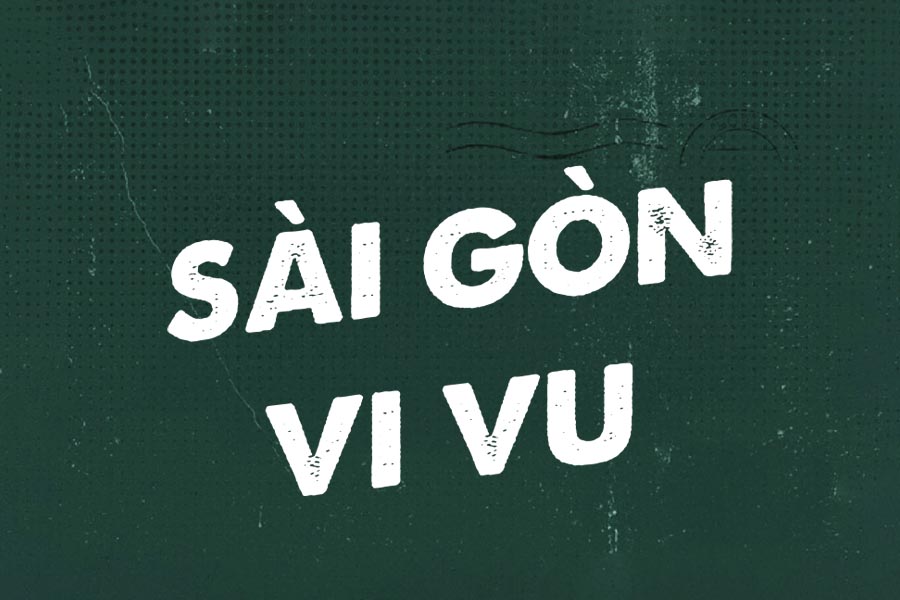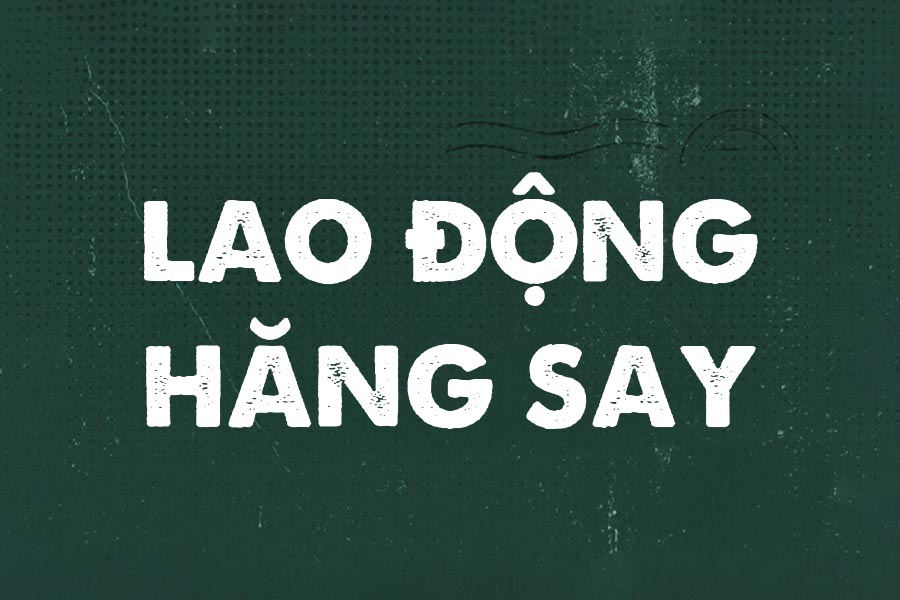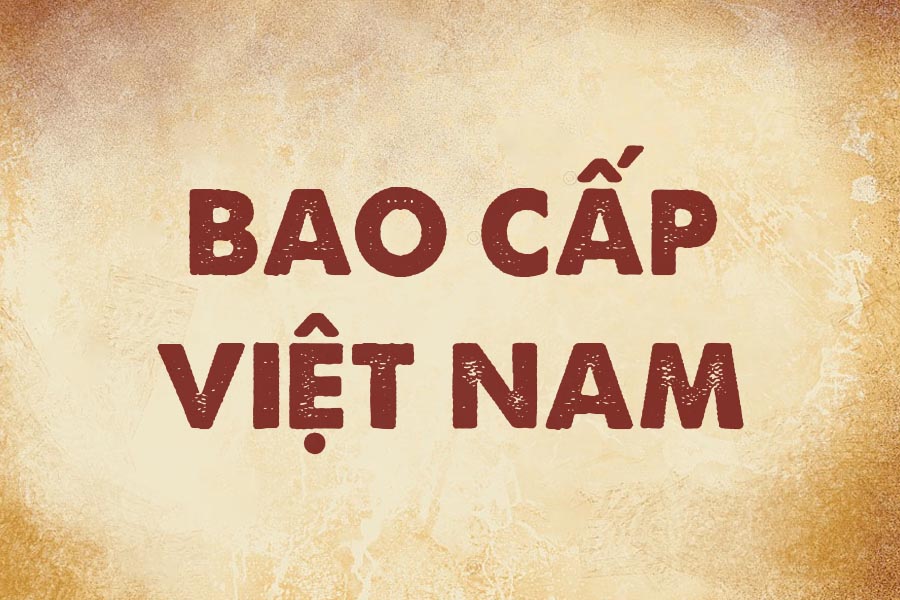
Bạn đang tìm một font chữ xưa, mang hơi thở thời kỳ bao cấp, gợi nhắc những tấm poster tuyên truyền hay khẩu hiệu treo đầu ngõ? Hãy thử ngay SVN-A Love of Thunder – một trong những font hoài cổ nổi bật nhất, mang đậm chất retro Việt Nam, được Việt hóa chỉn chu và miễn phí tải về.
Giới thiệu font SVN-A Love of Thunder
SVN-A Love of Thunder là font chữ display không chân, thiết kế theo phong cách áp phích tuyên truyền thời bao cấp với những nét chữ in đậm, rắn rỏi và hiệu ứng rách nhẹ như in trên giấy cũ. Các đặc điểm nổi bật:
• Toàn bộ chữ in hoa, tạo cảm giác cổ điển và cứng cáp.
• Nét chữ dày, đều, dễ đọc, lý tưởng cho tiêu đề hoặc slogan.
• Hiệu ứng grunge nhẹ, mô phỏng chất liệu in ấn thời xưa.
• Việt hóa hoàn chỉnh, hỗ trợ đầy đủ dấu tiếng Việt và ký tự đặc biệt.
Font chữ xưa gợi nhớ thời bao cấp
Không đơn thuần là một kiểu chữ, SVN-A Love of Thunder còn là một biểu tượng của ký ức. Font này gợi nhắc về giai đoạn bao cấp, nơi những câu khẩu hiệu như “Lao động là vinh quang”, “Đoàn kết là sức mạnh” được in đậm trên tường nhà máy, trường học, hợp tác xã…
Đó là lý do vì sao đây là font hoài cổ được rất nhiều designer lựa chọn cho:
• Poster cổ động, băng rôn tuyên truyền
• Bìa sách lịch sử, ấn phẩm văn hóa truyền thống
• Thiết kế vintage: tem phiếu, bao bì xưa, bảng tên hợp tác xã
Ứng dụng phong cách retro bao cấp trong thiết kế
SVN-A Love of Thunder là lựa chọn lý tưởng cho các thiết kế mang hơi thở xưa cũ, hoài cổ và thời kỳ bao cấp, cụ thể như:
• Poster tuyên truyền, tranh cổ động: Tái hiện khẩu hiệu như “Lao động là vinh quang”, “Đoàn kết là sức mạnh”.
• Bìa sách lịch sử – văn hóa: Phù hợp với sách nghiên cứu, hồi ký, tư liệu xưa.
• Ấn phẩm bảo tàng – triển lãm: Dùng cho tiêu đề, bảng chú thích, thiết kế trưng bày mang phong cách cổ điển.
Banner, băng rôn trường học: Rõ nét, dễ đọc, đúng chất tuyên truyền giáo dục thời bao cấp.
Thiết kế vintage khác: Tem phiếu, bao bì xưa, báo tường, mô phỏng thiết kế những năm 70–80.
SVN-A Love of Thunder không chỉ là một font chữ xưa, mà còn là một phần của lịch sử thị giác Việt Nam. Từ tấm poster tuyên truyền, slogan trên tường, đến bìa sách cổ – tất cả đều có thể sống dậy với font hoài cổ bao cấp này.
Nếu bạn đang làm dự án thiết kế cần cảm giác xưa cũ, chân thật và gợi cảm xúc, đừng bỏ lỡ font này.